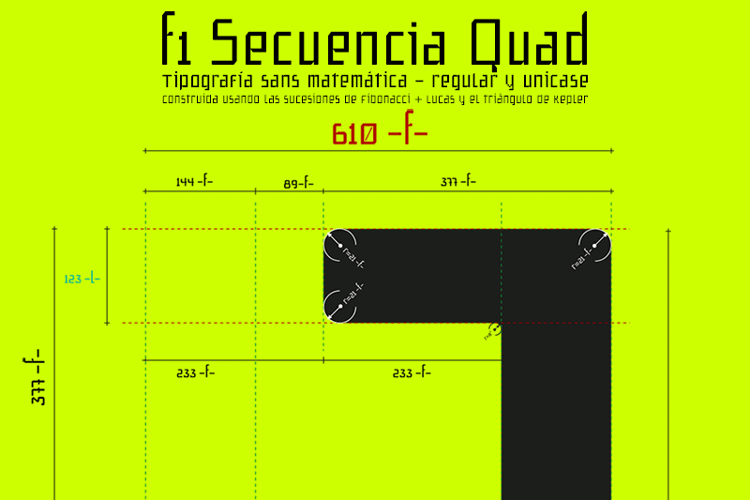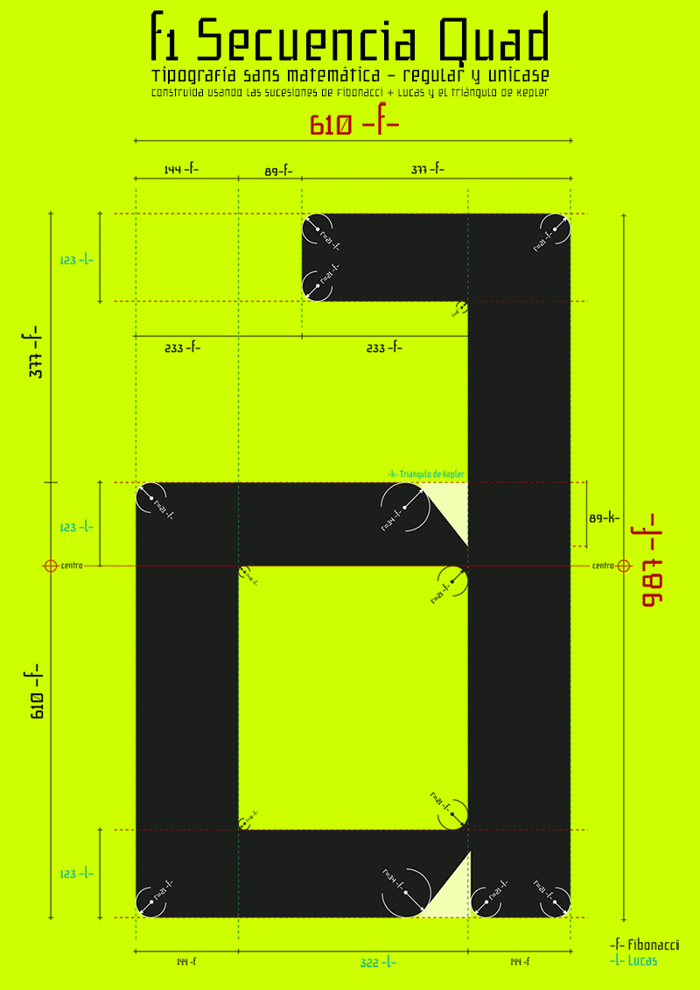
f1 Secuencia Quad ffp Font
Esta fuente es un experimento de proporciones, para definir todas ellas me he basado en la sucesiónes matemáticas de Fibonacci y Lucas, y para las hendiduras en los nudos de las astas y algunos signos de puntuación, he usado el triángulo de Kepler.
Todo el kerning y espaciado de la fuente está definido con las secuencias de Fibonacci, Lucas y Perri.
This typeface is an experiment in proportions to define all of them I have relied on the mathematical Fibonacci and Lucas sequences, and the slits at the nodes of the horns and some punctuation, I used the Kepler triangle.
All kerning and spacing of the source is defined sequences of Fibonacci, Lucas and Perri.
• Regular & Unicase